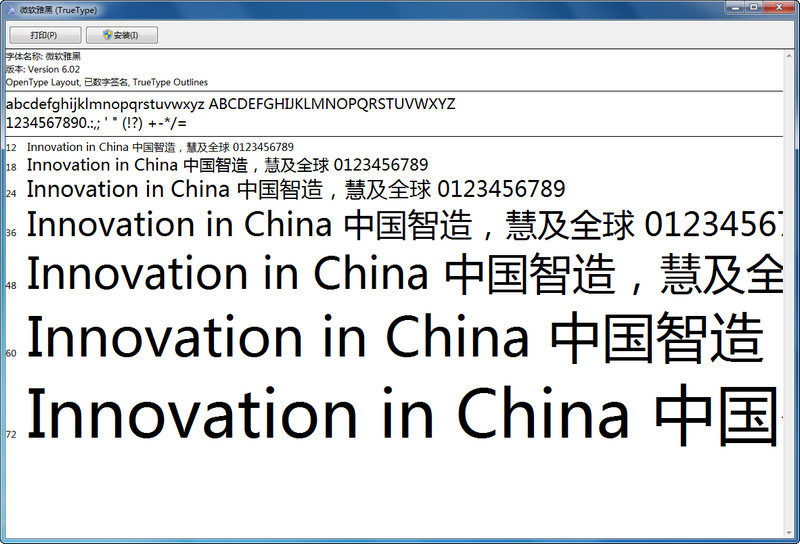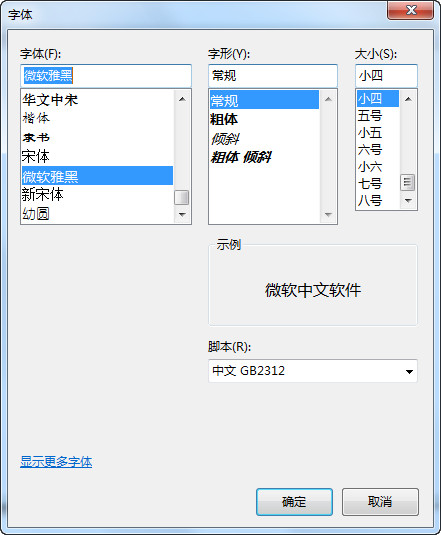
魔兽世界微软雅黑细字体
魔兽世界微软雅黑字体是微软官方推出的系统字体,常见于win7、xp、mac系统中,是一款使用广泛、造型大方的黑体字体,给人极佳的艺术视觉效果,欢迎大家来绿色资源网免费下载!
微软雅黑ttf是美国微软公司委托中国北大方正电子有限公司设计的一款全面支持ClearType技术的字体。Monotype公司负责字体Hinting工作。它属于OpenType类型,文件名是MSYH.TTF,字体设计上属于无衬线字体和黑体。这种字体每个字的造价成本在100美元左右。该字体家族还包括“微软雅黑Bold”(粗体),文件名为MSYHBD.TTF。这个粗体不是单纯的将普通字符加粗,而是在具体笔画上分别进行处理,因此是独立的一个字体。微软雅黑随简体中文版Windows Vista一起发布,是Windows Vista默认字体。另外,Microsoft office 2007简体中文版也附带这个字体。
在涵盖的字库上,微软雅黑支持GBK字符集,包含了Unicode的所有 20902个中文字符以及中国国家标准化组织添加的大约 80个中文字符,还包含了Big5的繁体中文字符和GB2312中的简体中文字符。
微软雅黑体是一款全新的支持 ClearType技术的中文界面显示字体浮出水面,这就是微软雅黑体。
这款字体是一种全新的无衬线黑体,它的字形略呈扁方而饱满,笔画简洁而舒展,易于阅读。这款字体在 ClearType 技术下的清新和优美着实给人留下了深刻的印象。同时,微软方面也为这种新型字体付出了昂贵的代价。“这种字体每个字的造价成本在100美元左右,据不完全统计,我国各字典、词海收录有2万多个汉字”。
微软雅黑字体特点
1. 单独设计的粗体。
2. 显示品质优异的斜体。
3. 更清晰的小号字显示。
4. 对于最常用的字号。
5. 更优美而现代的字形设计。